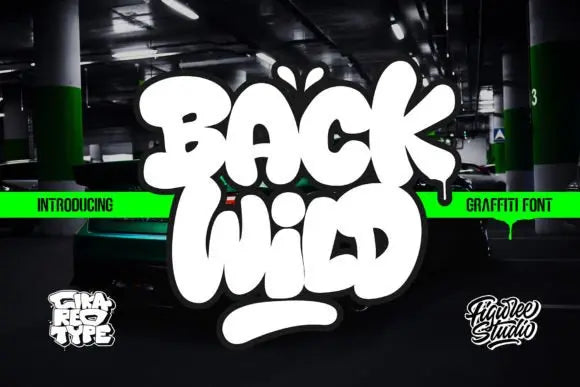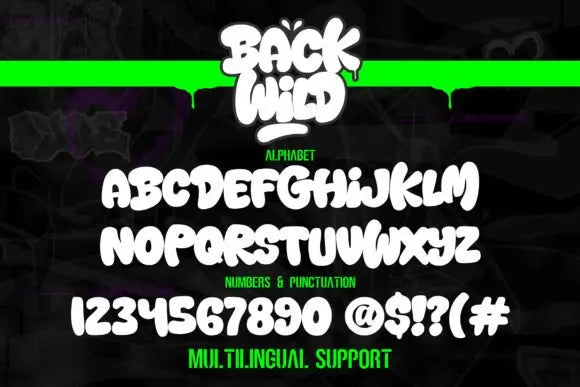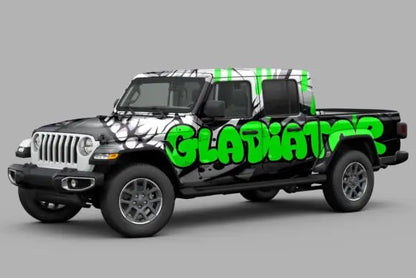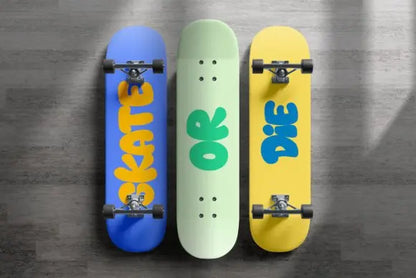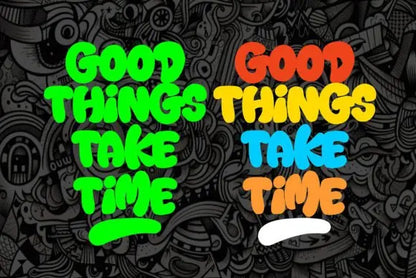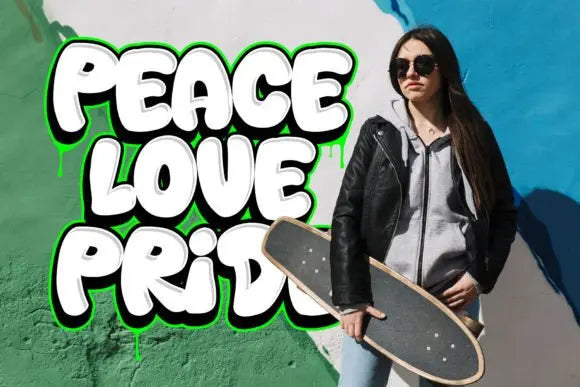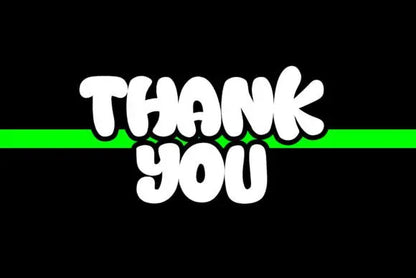
Volver fuente salvaje
“Back Wild” es una fuente de graffiti atrevida y rechoncha que incluye caracteres swash. Las fuentes con estos atributos generalmente presentan formas de letras anchas y en negrita, a menudo con elementos divertidos y redondeados.